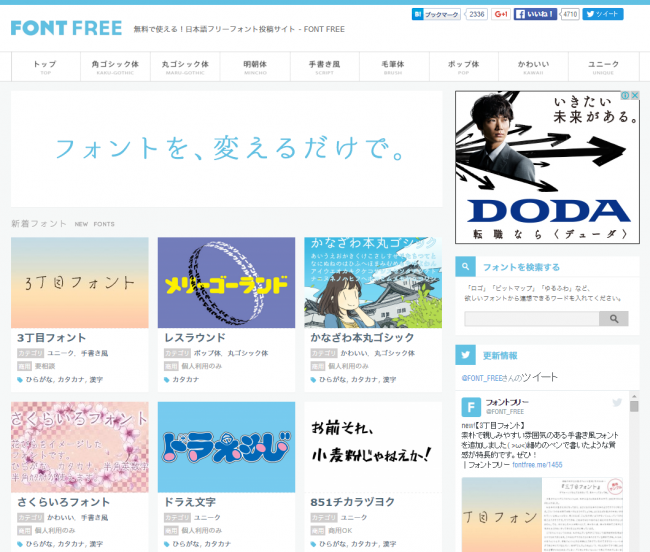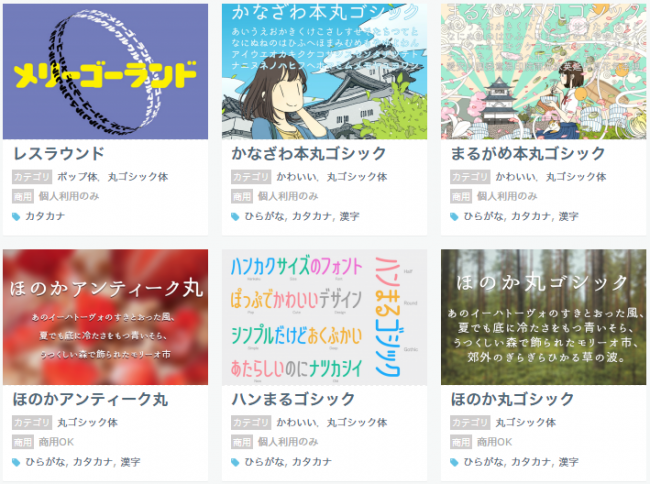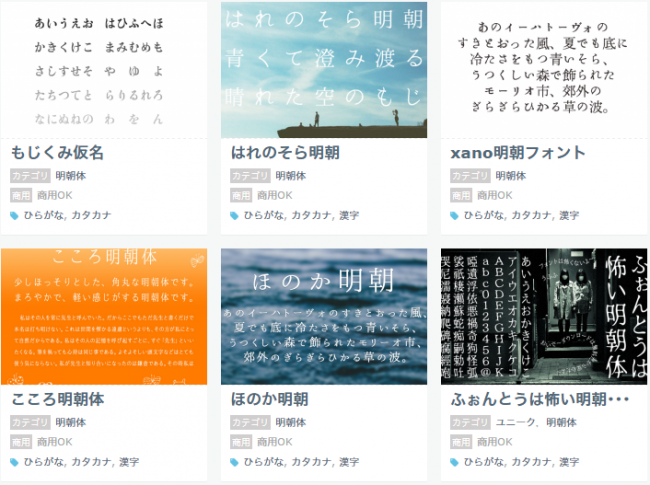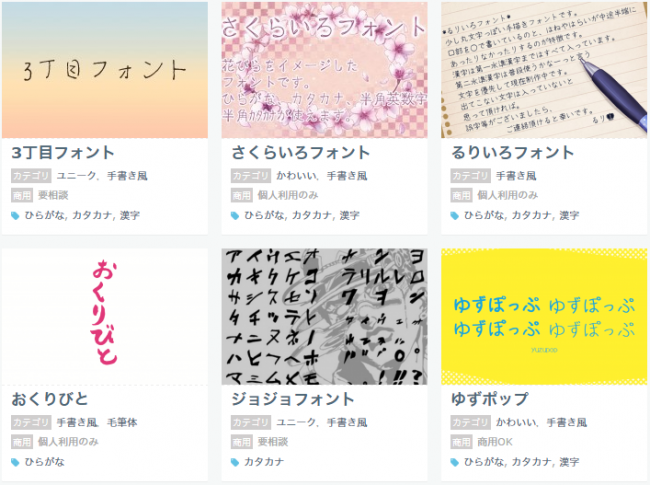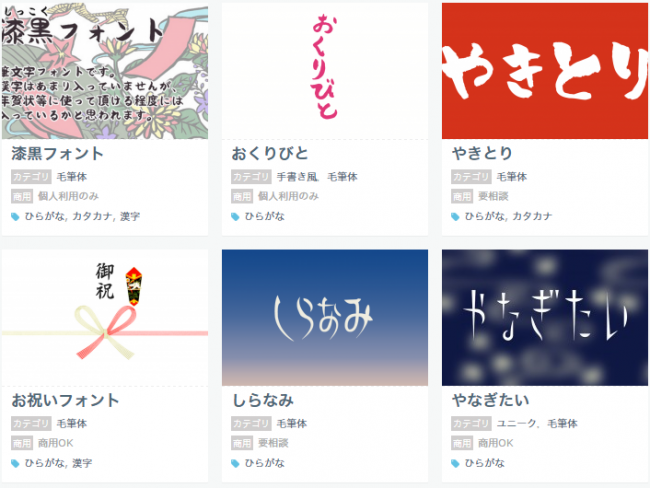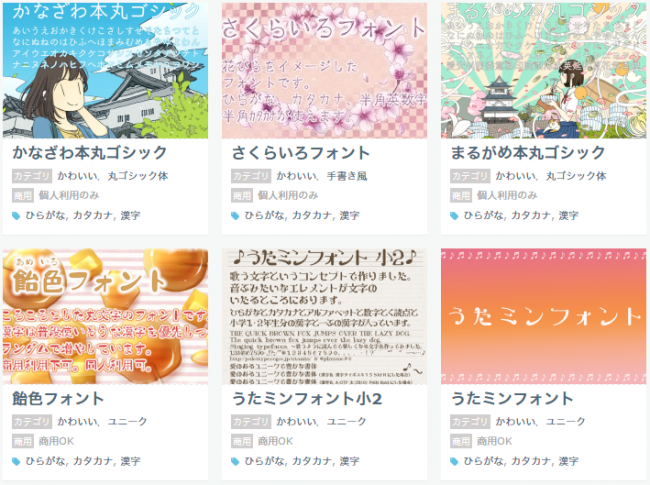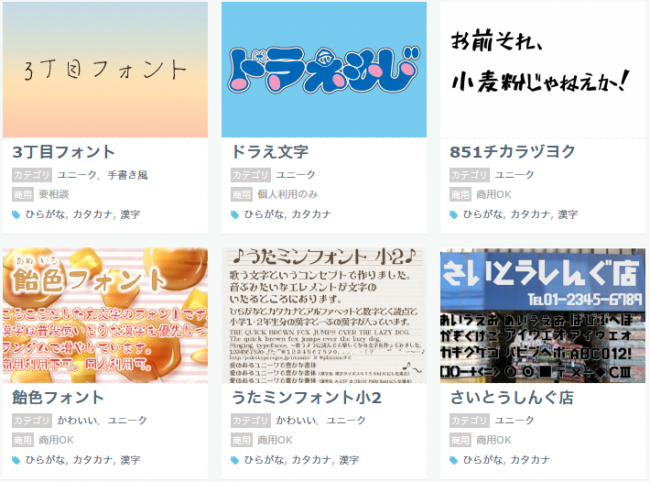
日本語フォントを探せるフォントまとめサイト Font Free
Font Freeは日本語フォントを探せるフォントまとめサイトです。
漢字やカタカナ、ひらがなが使える日本語フォントを、明朝体、ゴシック体、手描き風、ポップ体、かわさいいなどのカテゴリから探すことができます。
200個以上の日本語フォントが紹介されています。
角ゴシック
角ゴシック体(かくゴシックたい)、またはゴシック体とは、サンセリフの書体(漢字、かな)のことをいう。丸ゴシック体と分別するために角ゴシック体と表記する場合がある。縦横の太さが均等であるのが特徴。
丸ゴシック体
丸ゴシック体(まるゴシックたい)は、ゴシック体と同じくほぼ均一な太さの点画で構成されるが、その画の両端や曲がりなどが丸まった書体である。
明朝体
明朝体(みんちょうたい)は、セリフ書体に分類される、漢字や仮名の表示において標準的な書体である。
おもに長文においての可読性が高い。
手書き風
手書き風(てがきふう)は、名前の通り手書きのような書体のこと。こどもが書いたような文字や、女の子が書いたような文字などがある。
毛筆体
毛筆体(もうひつたい)とは、毛筆で書いたような書体の総称のことをいう。和風なデザインや、上品なデザインにも使える書体です。
ポップ体
ポップ体と、ポップ調なフォントも分類してあります。親しみやすく、可愛らしいデザインをする際に便利な書体です。
かわいいフォント
可愛いフォントはここに分類しています。女の子らしい、かわいいデザインをする際使えるフォントです。
ユニークなフォント
他書体に当てはまらなかったちょっと個性的な書体(デザイン書体や変わっているもの)はここに分類してあります。ユニークで、インパクトのあるフォントを集めました。